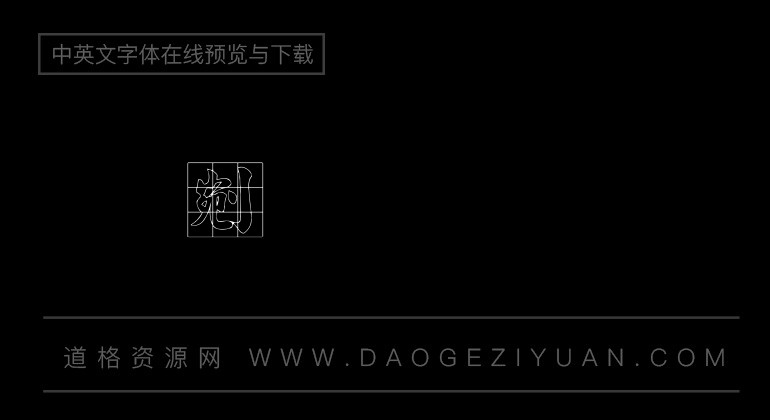
金梅毛正楷九宫字
金梅毛正楷九宫字是一种九宫格字体,它以梅花为灵感,将梅花的线条细节融入到字体中,使字体看起来更加精致、清新。它具有细腻的线条,字体的比例设计得当,让人可以非常容易地识别字体。此外,它也具有良好的可读性,可以帮助读者更容易理解文字的含义。
金梅毛正楷九宫字是一款非常不错的手写艺术字体,具有很好的视觉感,适合于文化类的宣传设计、商业类品牌的广告和产品包装设计以及个性化文字排版等较多场景。